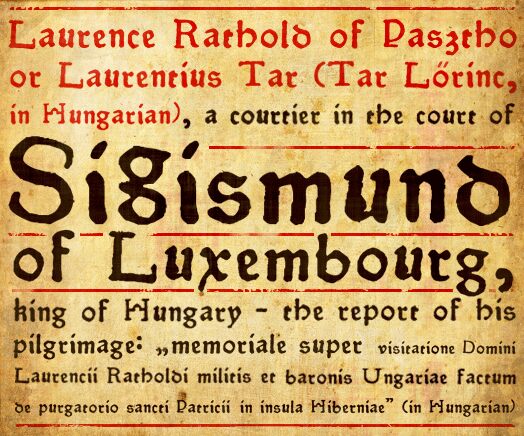
Pokoljaro von Bumbayo Font Fabrik ist eine kostenlose, erodierte Display-Schrift mit stumpfen, handgeschnittenen Buchstabenformen. Ihre Kanten sind ungleichmäßig mit holprigen Verbindungen und Dellen.
Abgenutzte Illustrationen, im Blockdruckverfahren erstellte Muster und handgemachte Markierungen können ihre raue Textur auf Plakaten und Musikverpackungen ergänzen. Dieselben groben Formen passen zu Horror-Event-Grafiken und Spieletiteln, insbesondere für Volksmärchen, zerstörte Kulissen oder düstere Comicszenen in einem rauen, Low-Budget-Grafikstil.